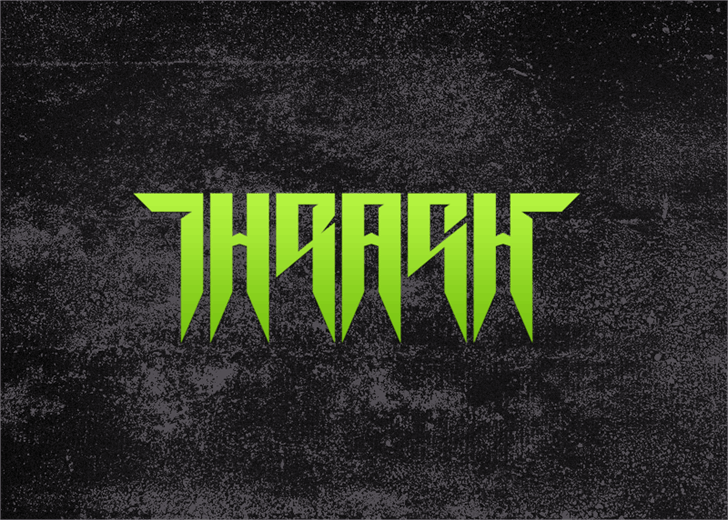
A fonte Thrash it é uma escolha perfeita para designers que procuram algo moderno, dinâmico e com forte personalidade. Sua linhas levemente afiadas e desenhos de traço aparentemente incisivos criam um visual agressivo e inovador, tornando-a ideal para qualquer aplicação onde deseja destacar seu texto ou criar um impacto poderoso. Essa fonte foi projetada pelo designer Hamilton, oferecendo uma combinação única de beleza e força que se encaixa perfeitamente em títulos, design editorial e até mesmo em artesanato. Com sua categoria como fontes simbólicas, Thrash it é a escolha ideal para quem busca um estilo marcante que destaca sua personalidade criativa. Descubra o potencial inegável de uma fonte tão poderosa – seu próximo grande projeto pode precisar dela!